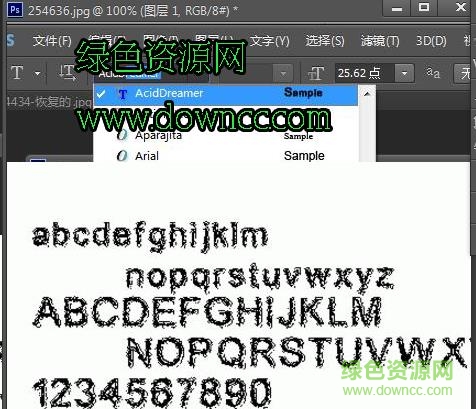
aciddreamer通過(guò)是一款能夠?qū)⑦呇貙?shí)現(xiàn)顆?;l(fā)散效果的字體樣式,十分好看,讓你能夠運(yùn)用到游戲創(chuàng)作中,如游戲的出場(chǎng)字母與結(jié)束字母的運(yùn)用,當(dāng)玩家觀看到帶來(lái)特色效果的aciddreamer字體樣式定會(huì)獲得一種視覺(jué)享受!